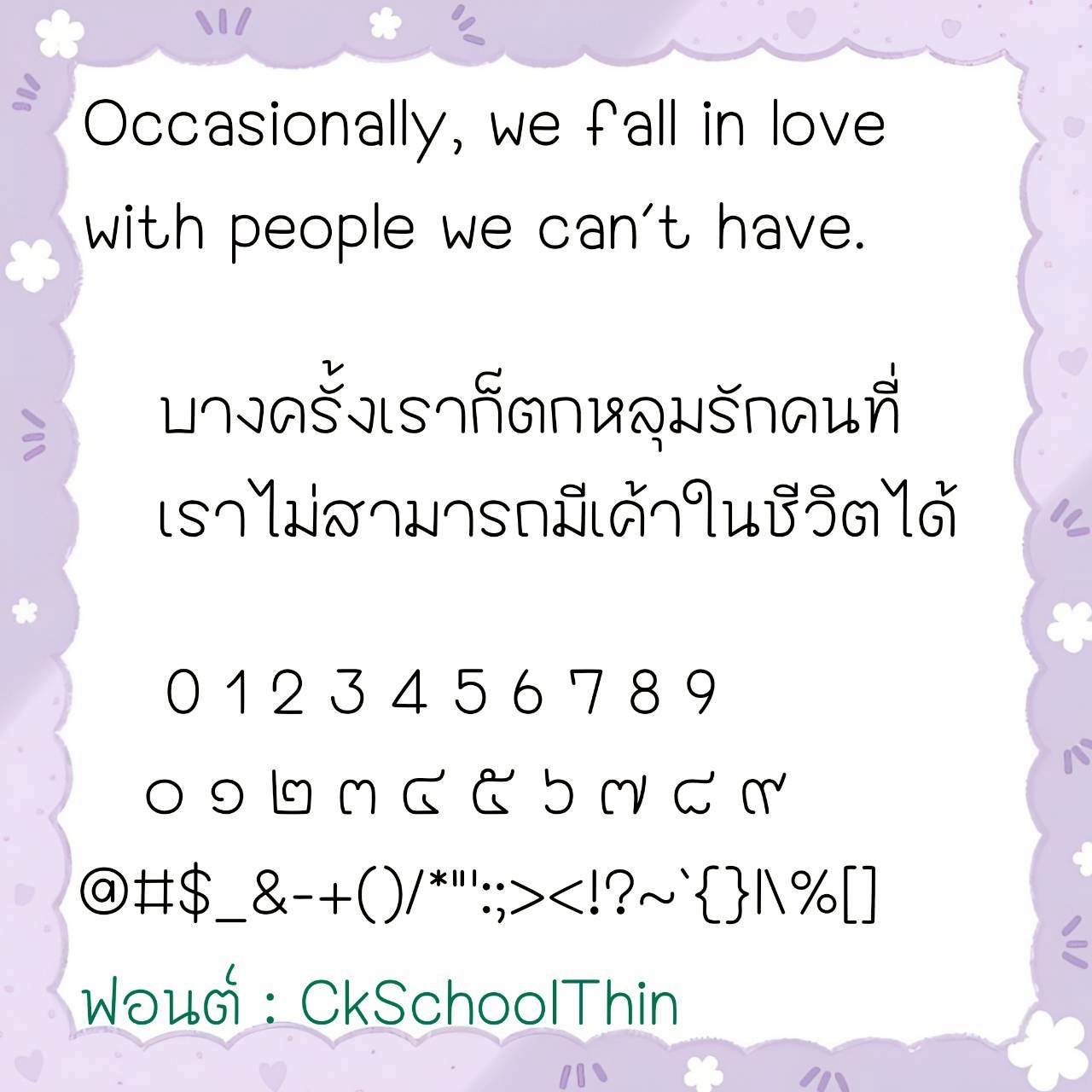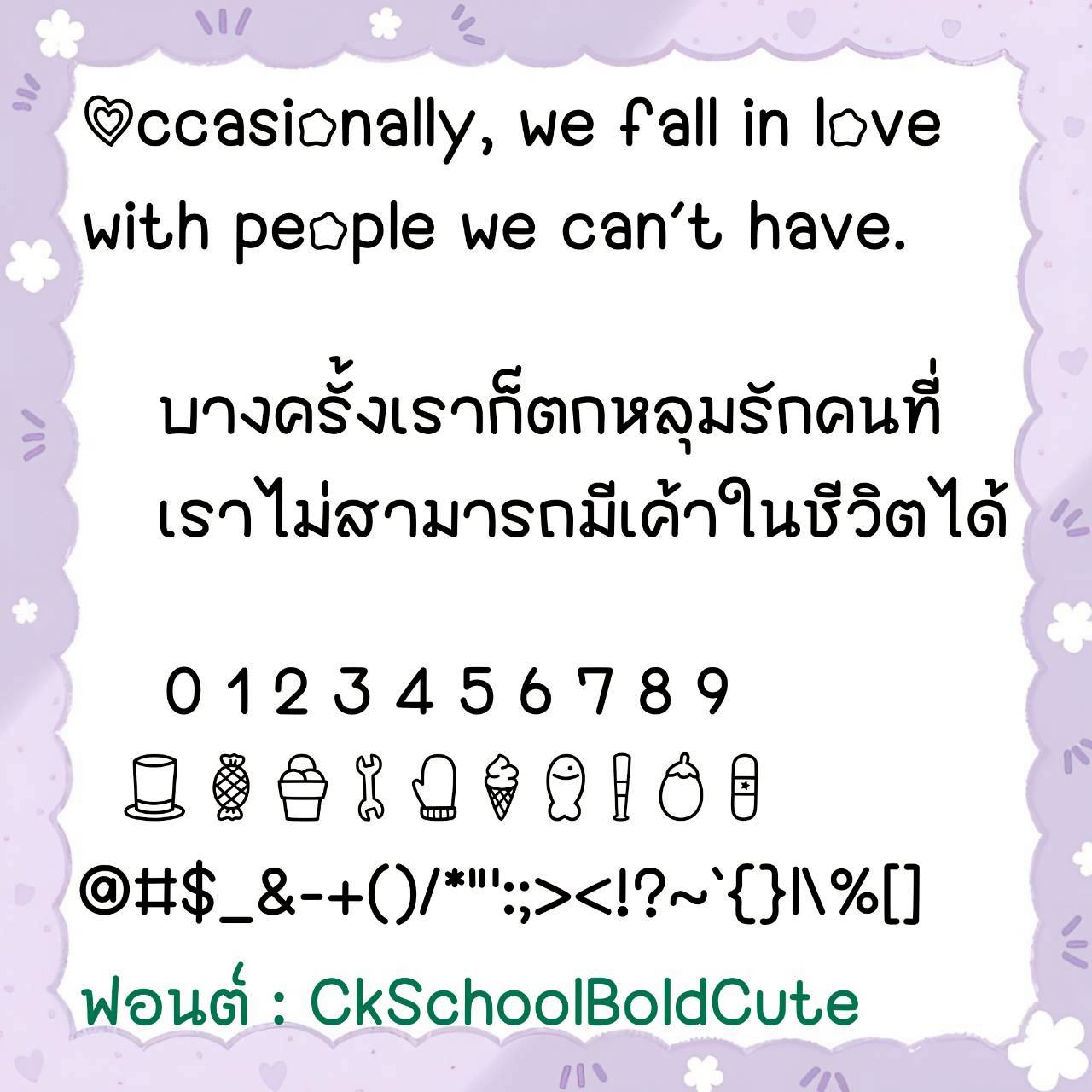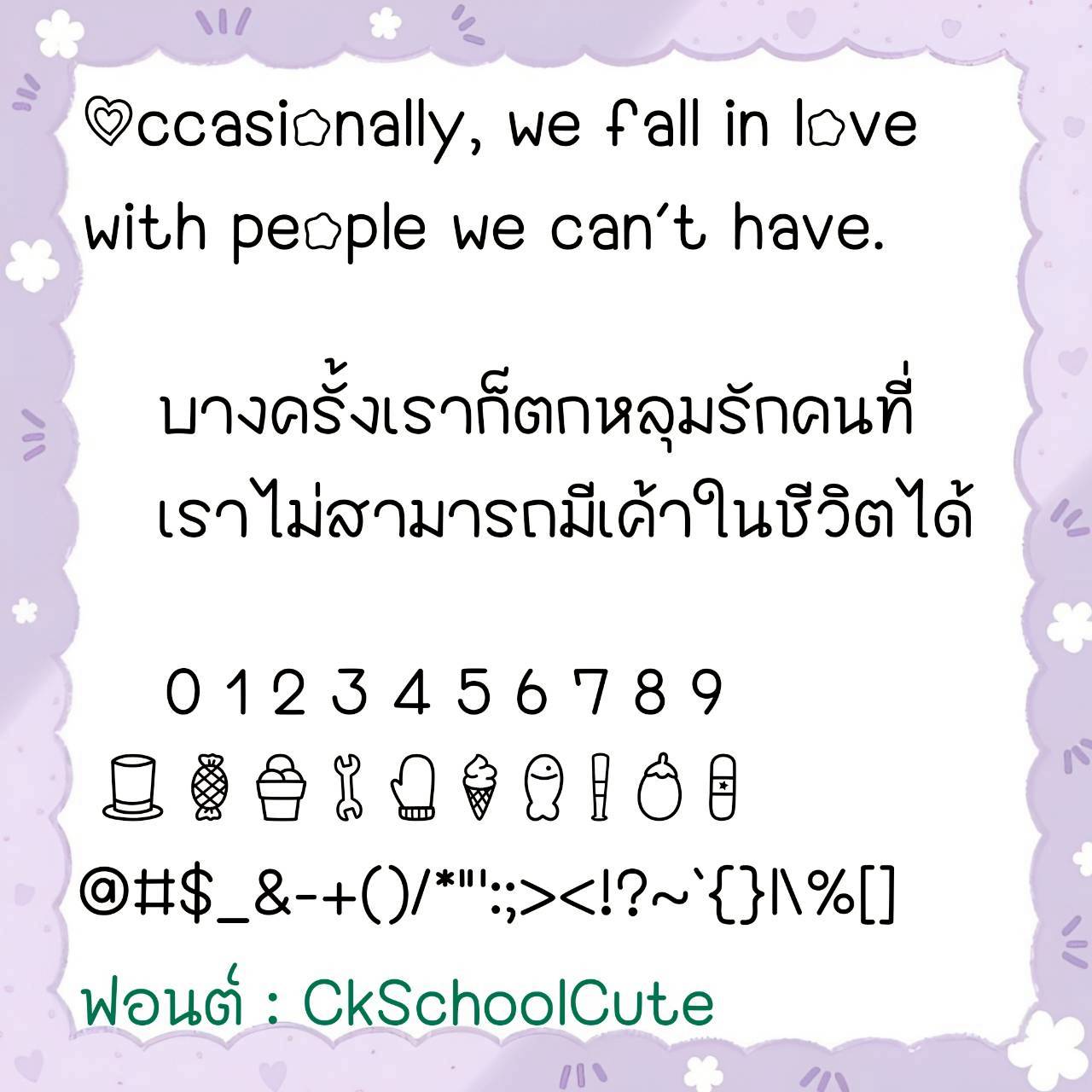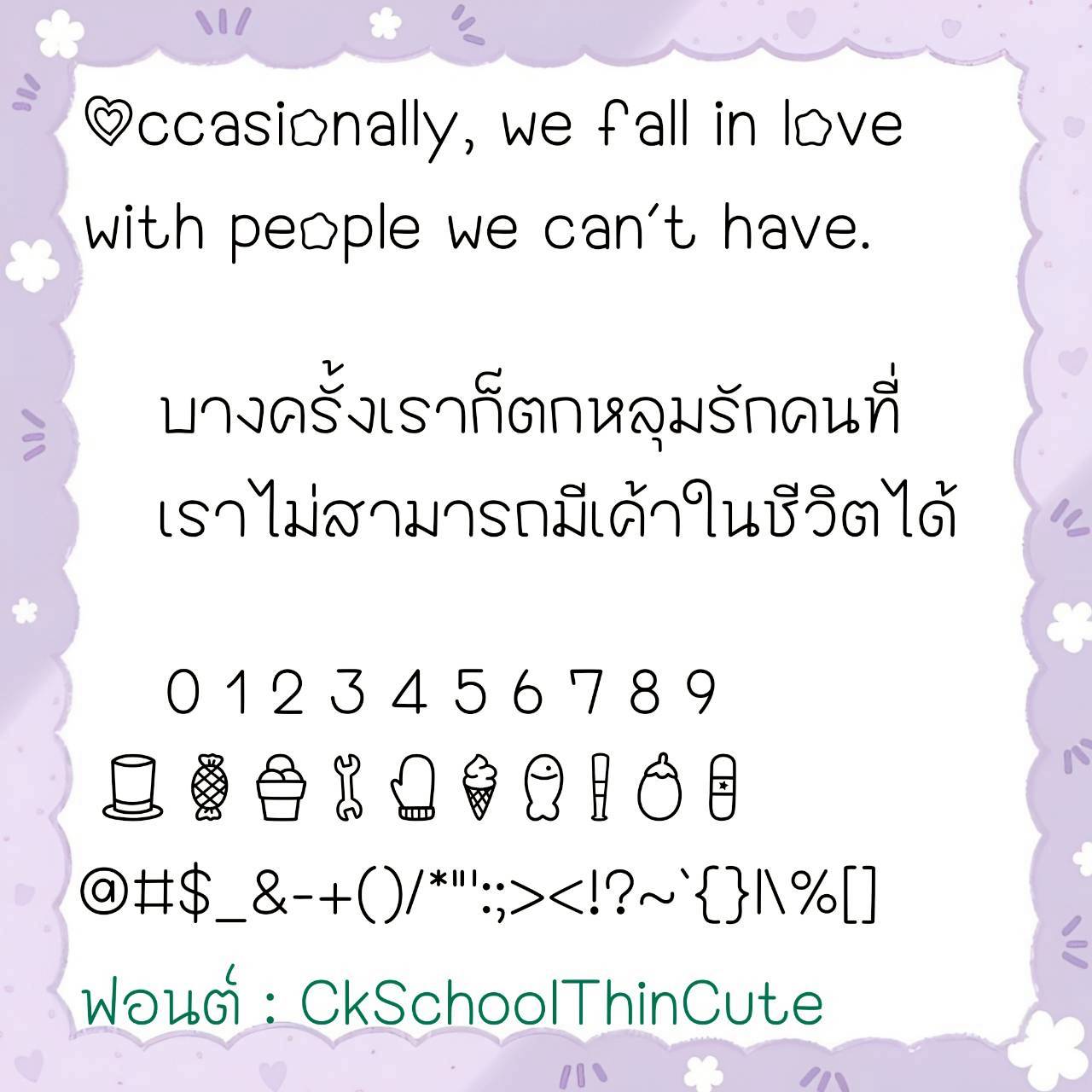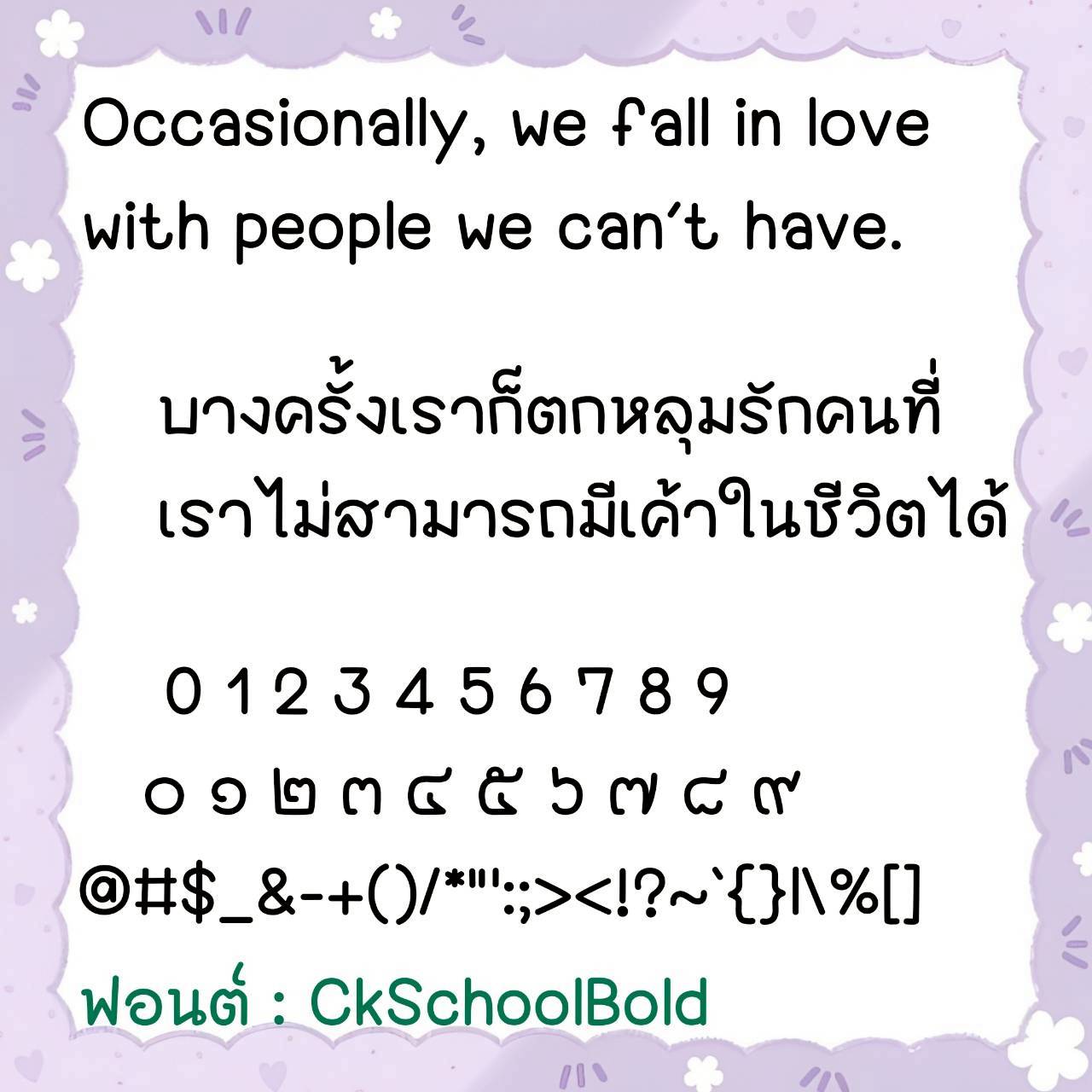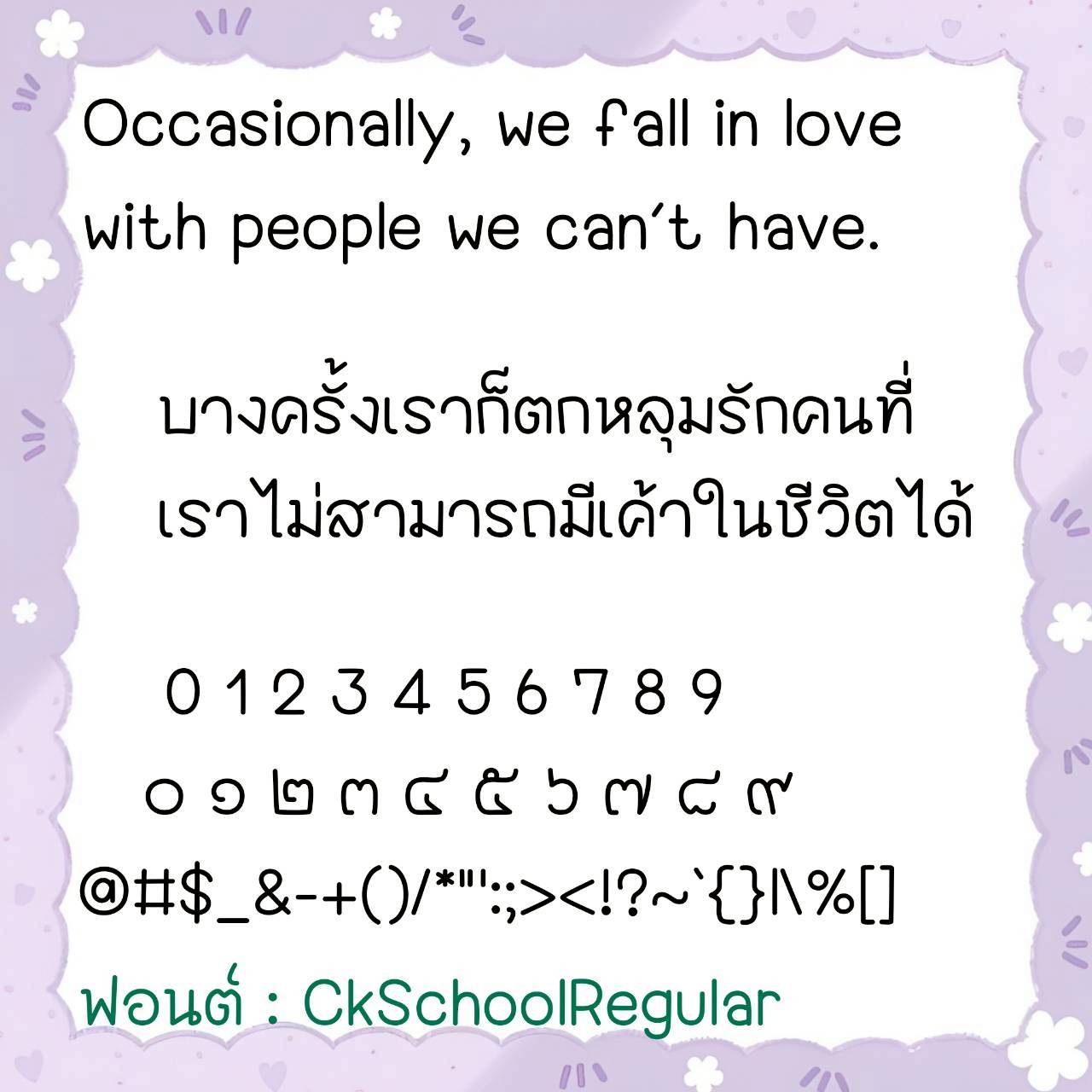
Font CkSchool
ชื่อสินค้า : Font CkSchool 💙
🔸 ฟอนต์ลายมือแนวไม่มีหัว ตัวอวบอ้วน เน้นความเป็นระเบียบ เน้นอ่านง่ายสบายตา และยังมีไฟล์อิโมจิน่ารักๆที่ใช้แทนเลขไทยให้ด้วยค่ะ 🥰💙
🔹 This is a handwritten font with no sans-serifs, chubby characters, emphasizing neatness, readability, and ease of viewing. It also includes cute emoji files that can be used to replace Thai numerals. 🥰💙